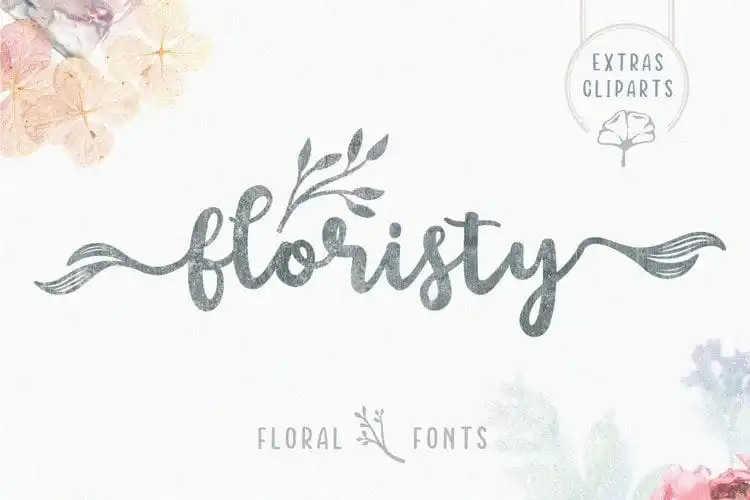
Floristy Script Font – Download Grátis
Descubra Floristy Script Font, uma elegante tipografia floral que destina-se a ser sua nova amiga. Inspirada nas designs de águacolor e flores, esta fonte é um convite para combinar texturas florais e linhas finas num estilo sofisticado e delicado. Perfeita tanto para as etiquetas de seu produto quanto para os materiais pessoais como cartões, encomendas e invitations, Floristy Script Font também se destaca em plataformas digitais como o YouTube e como elemento principal nos seus posts nas redes sociais. Seja você um designer ou uma pessoa que quer dar um toque personalizado a seu trabalho digital, esta fonte pode ser um complemento ideal para qualquer estilo de design.